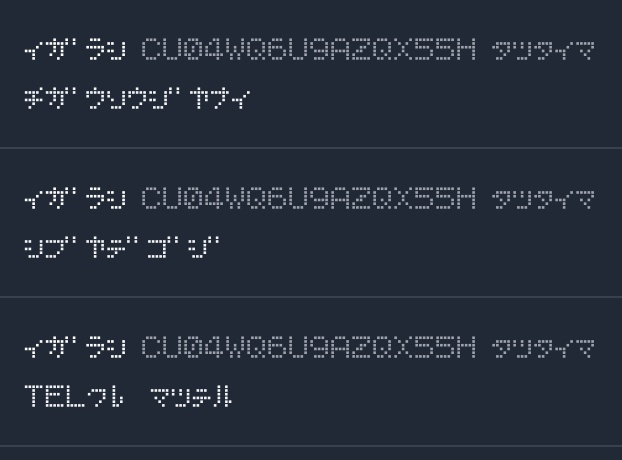
503 bad gatewayBellPokeフォントDigital0 JPY免費下載bellpoke_fonts.zip (9.8 KB)bellpoke_fonts.zipAbout Giftポケベル風フォント。 https://bellpoke.date50.net/ で使っているものです。 以下が収録されています。 ・アルファベット(大文字) ・半角カタカナ(小文字なし) ・半角数字 ・記号(?!#&-) 細かな動作確認はしていませんが、よかったらご利用ください。 <ご利用に当たって> ・商用問わず好きに使っていただいてOKです。 ・使ったことをXで @503_bad 宛に報告してくれると喜びます。 ・Webフォントとしての利用もOKです。 ・直接的な再配布はやめてください。 503 bad gatewayVisit FANBOX!SoftwareFxChainTools - ノイズ除去も簡単!OBS用 音声整えエフェクトチェイン プラグイン503 bad gateway1,000 JPYViewM3-2026SpringMusic (General)【14thアルバム】Prophesied【メロディックハード/ヘヴィメタル】M3春-2026503 bad gateway2,000 JPYViewM3-2025AutumnMusic (General)【13thアルバム】OracLE【メロディックハード/ヘヴィメタル】M3秋503 bad gateway2,000 JPYSoftwareLiveReaction Fighter503 bad gateway300 JPYT-Shirts503クジラTシャツ(黒)503 bad gateway2,500 JPYT-Shirts503ビッグくじらTシャツ(黒)503 bad gateway2,500 JPYT-Shirts503クジラTシャツ(白)503 bad gateway1,850 JPYT-Shirts503ビッグくじらTシャツ(白)503 bad gateway1,850 JPYM3-2026SpringGoods (Other)Out of Stock【特級呪物爆誕】伊達五十嵐 生首きんちゃく503 bad gateway2,000 JPYAccessories (Other)Out of Stock伊達五十嵐アンブレラマーカー503 bad gateway1,200 JPYViewM3-2025springMusic (General)【12thアルバム】Lightning【メロディックハード/ヘヴィメタル】503 bad gateway2,000 JPYViewM3-2023autumnMusic (General)Out of Stock【9thアルバム】POWER_CODE503 bad gateway1,500 JPYM3-2024autumnAccessories (Other)Out of Stock伊達五十嵐 生首ヘアゴム(2個セット)503 bad gateway1,500 JPYViewM3-2024autumnMusic (General)Out of Stock11thアルバム MySOUL503 bad gateway1,500 JPYM3-2024springMusic (General)Out of Stock【10thアルバム】Next Round503 bad gateway1,500 JPYM3-2023springMusic (General)Out of Stock【8thアルバム】Stay agile503 bad gateway1,500 JPYAcrylic Figure伊達五十嵐 アクリルフィギュア(イラスト版)503 bad gateway2,700 JPYAcrylic Figure伊達五十嵐 アクリルフィギュア(ソロイラスト版)503 bad gateway2,700 JPYTote bagsVTuber伊達五十嵐 イラストトートバッグ503 bad gateway1,630 JPYGlasses & Tumblers & Mugs伊達五十嵐イラストマグカップ503 bad gateway1,850 JPY查看更多